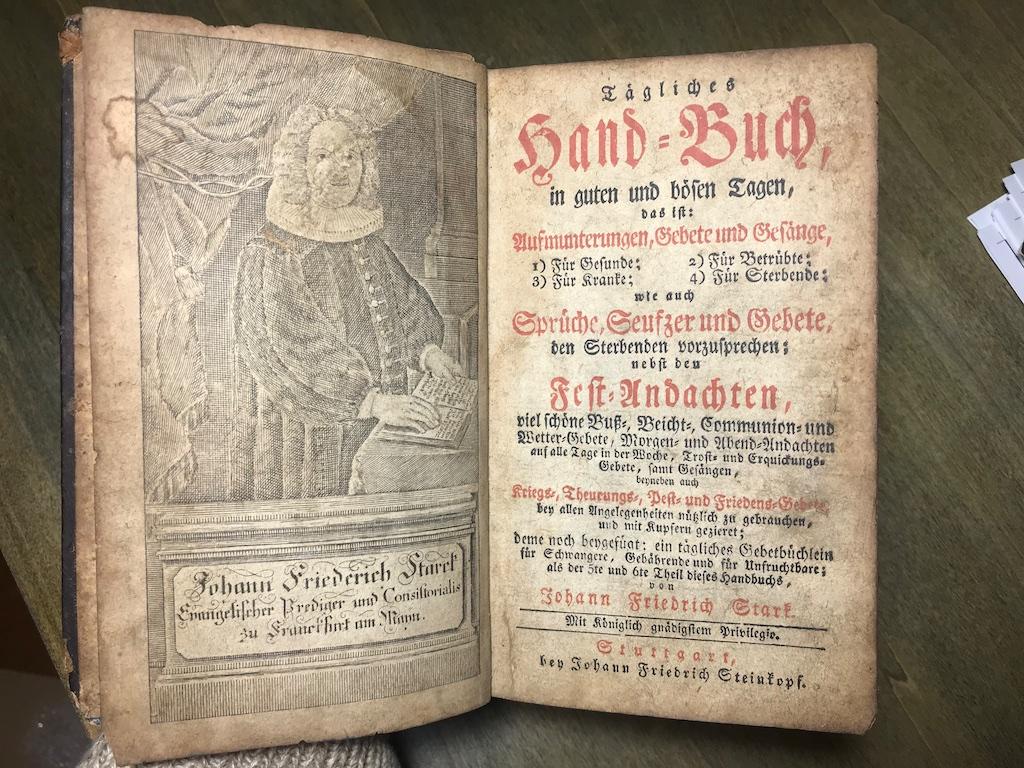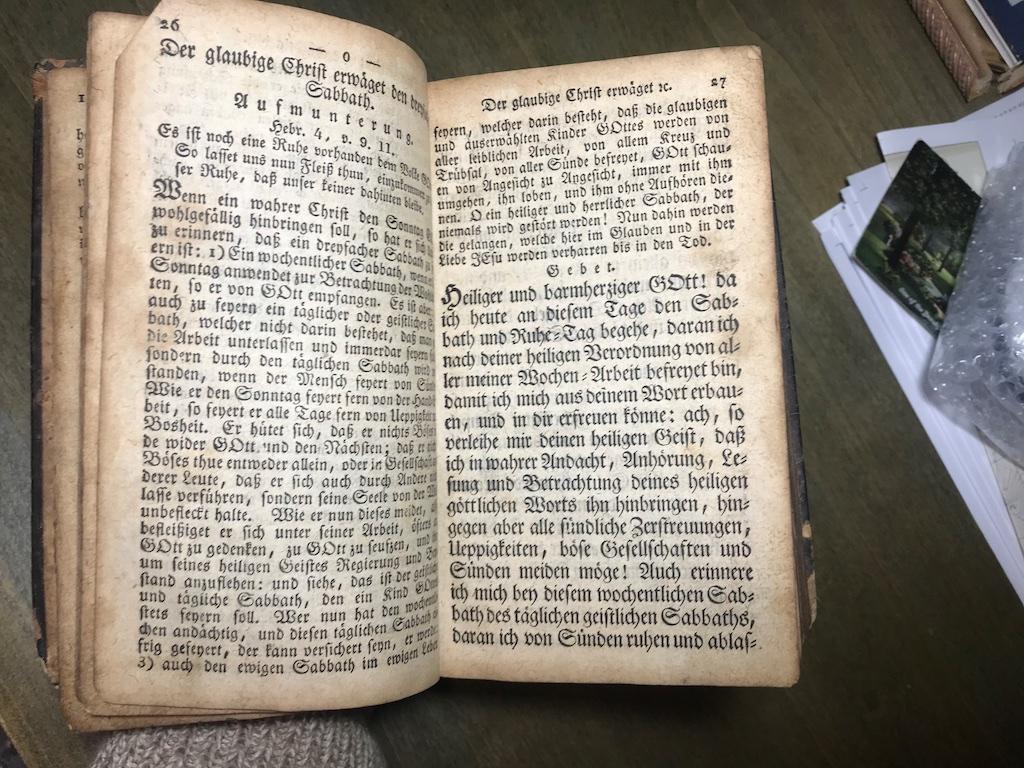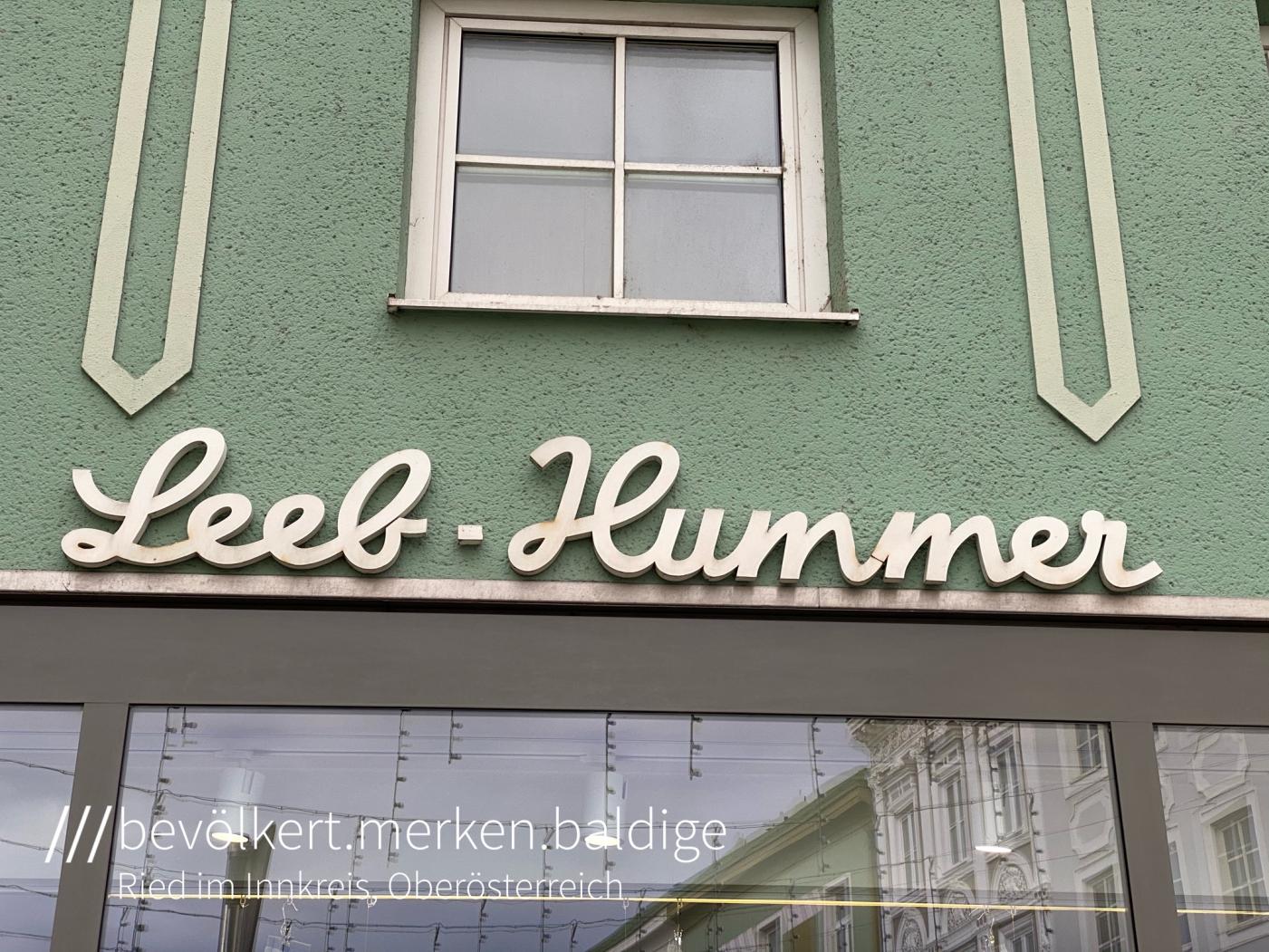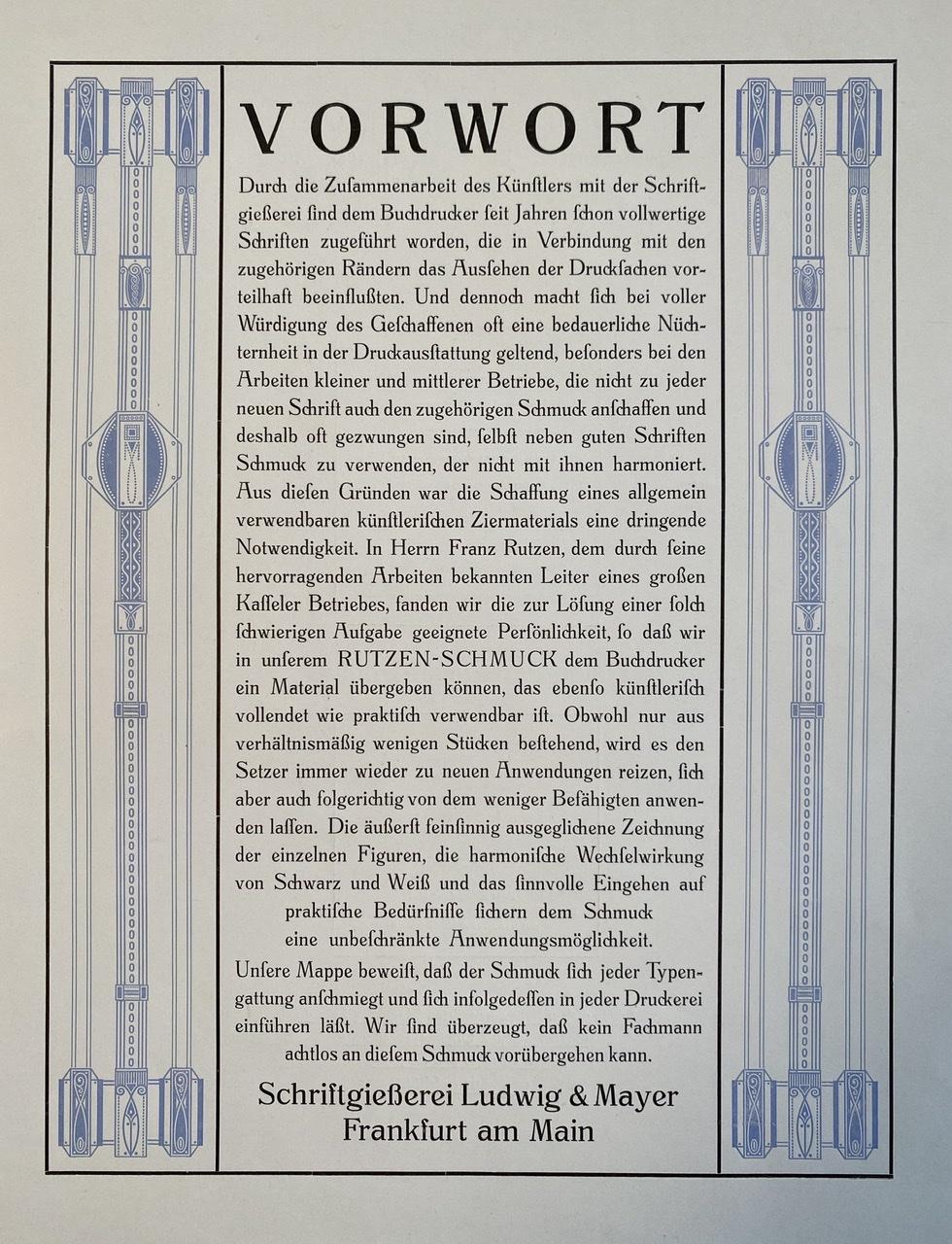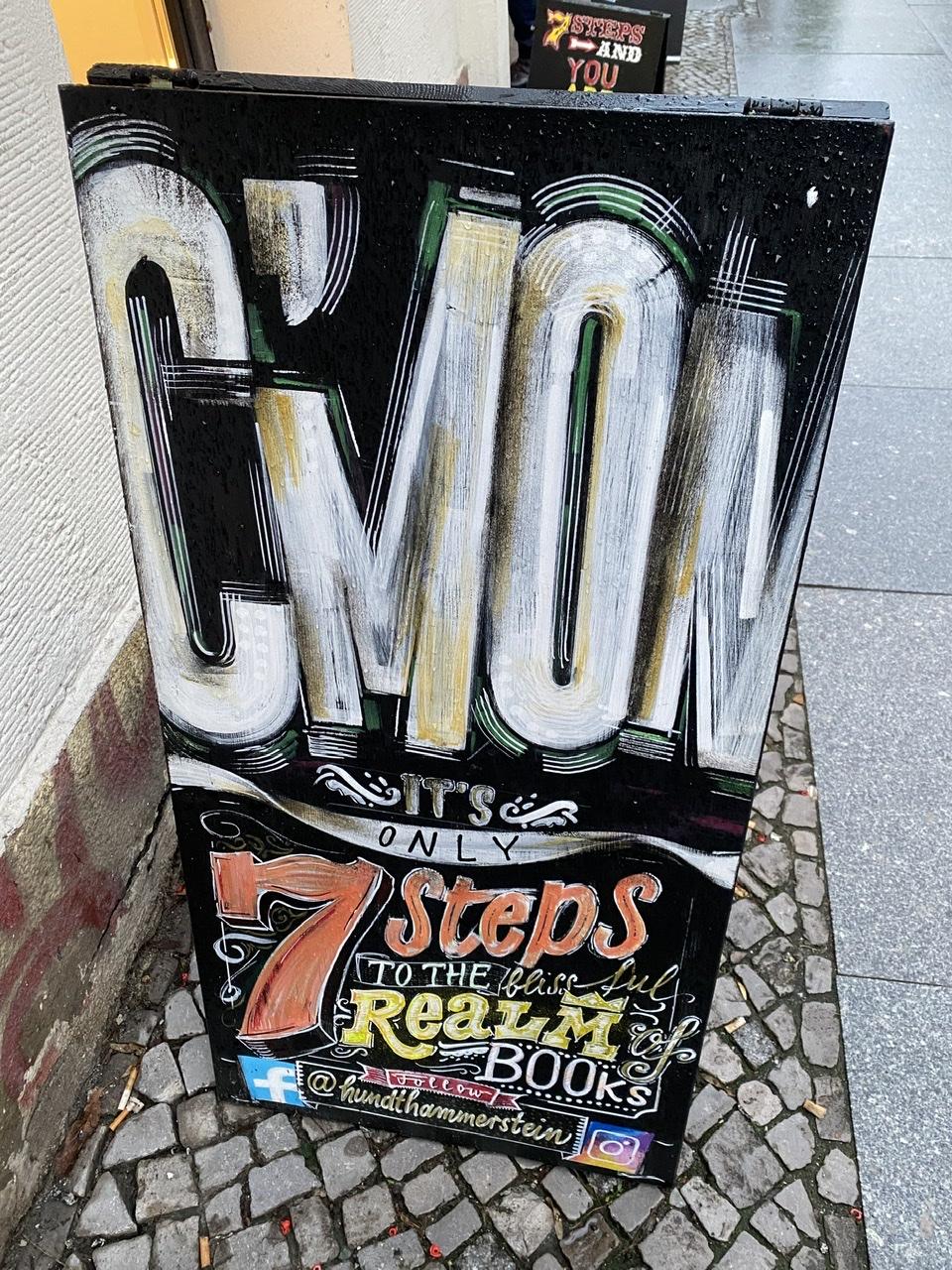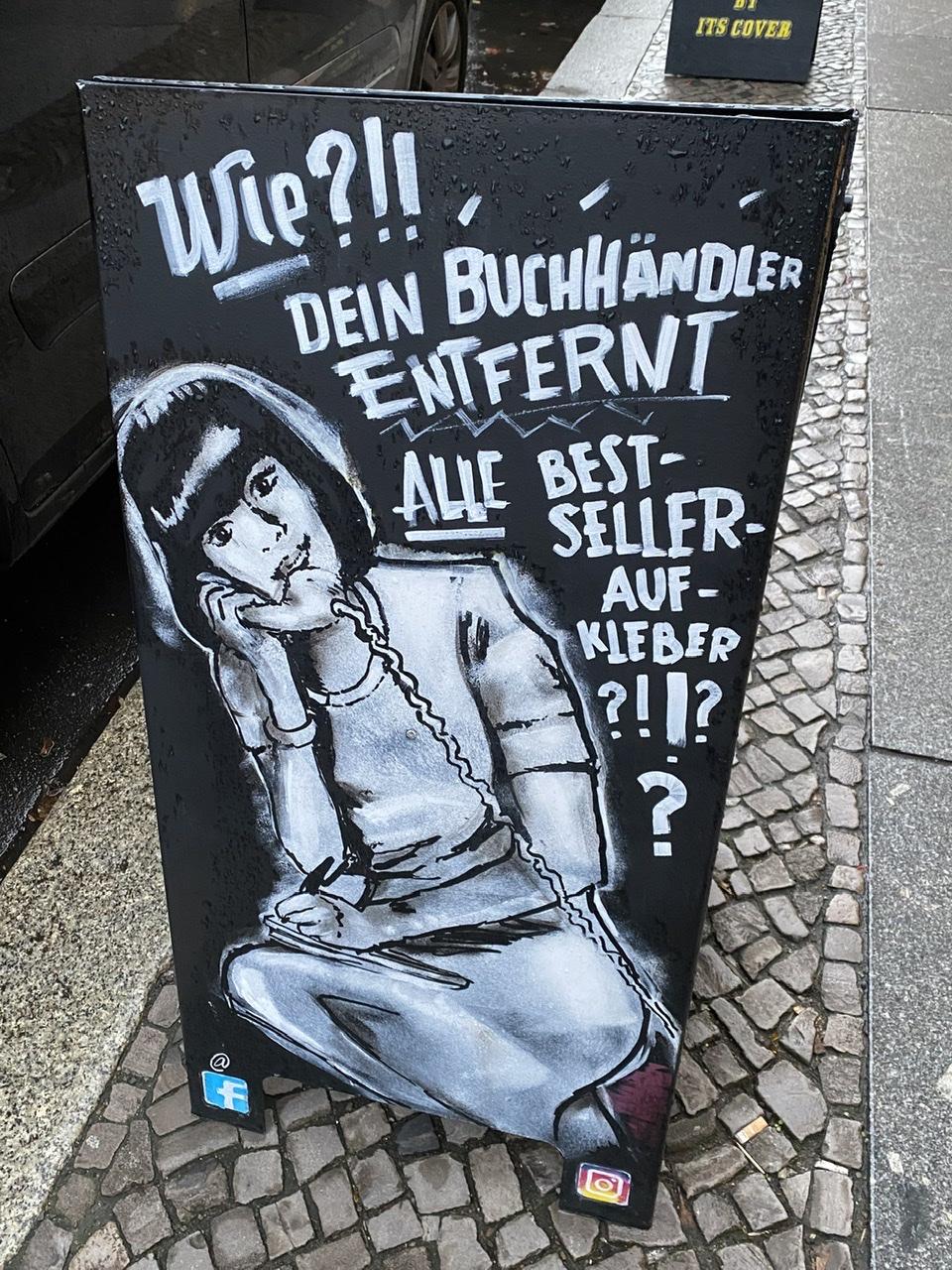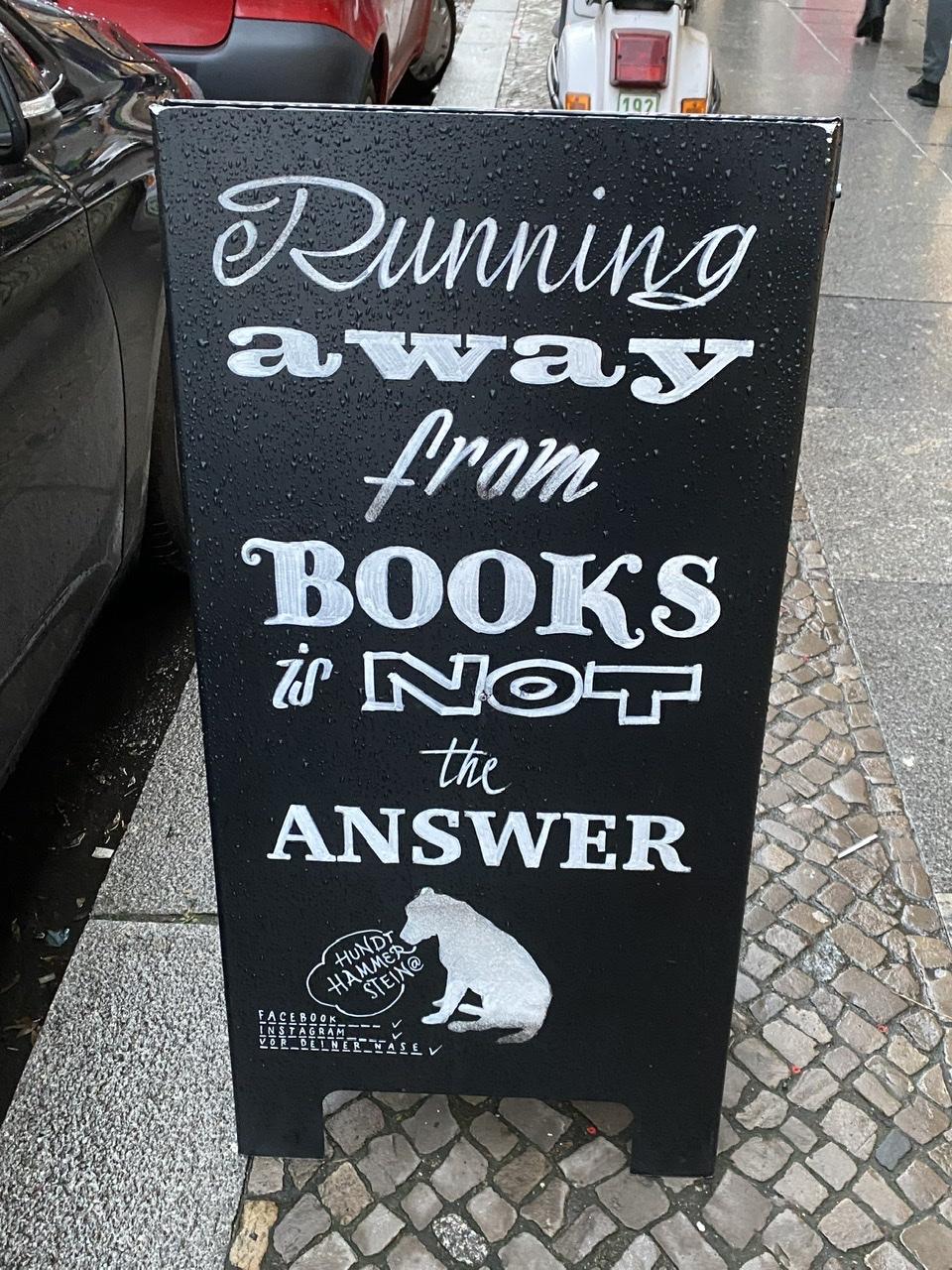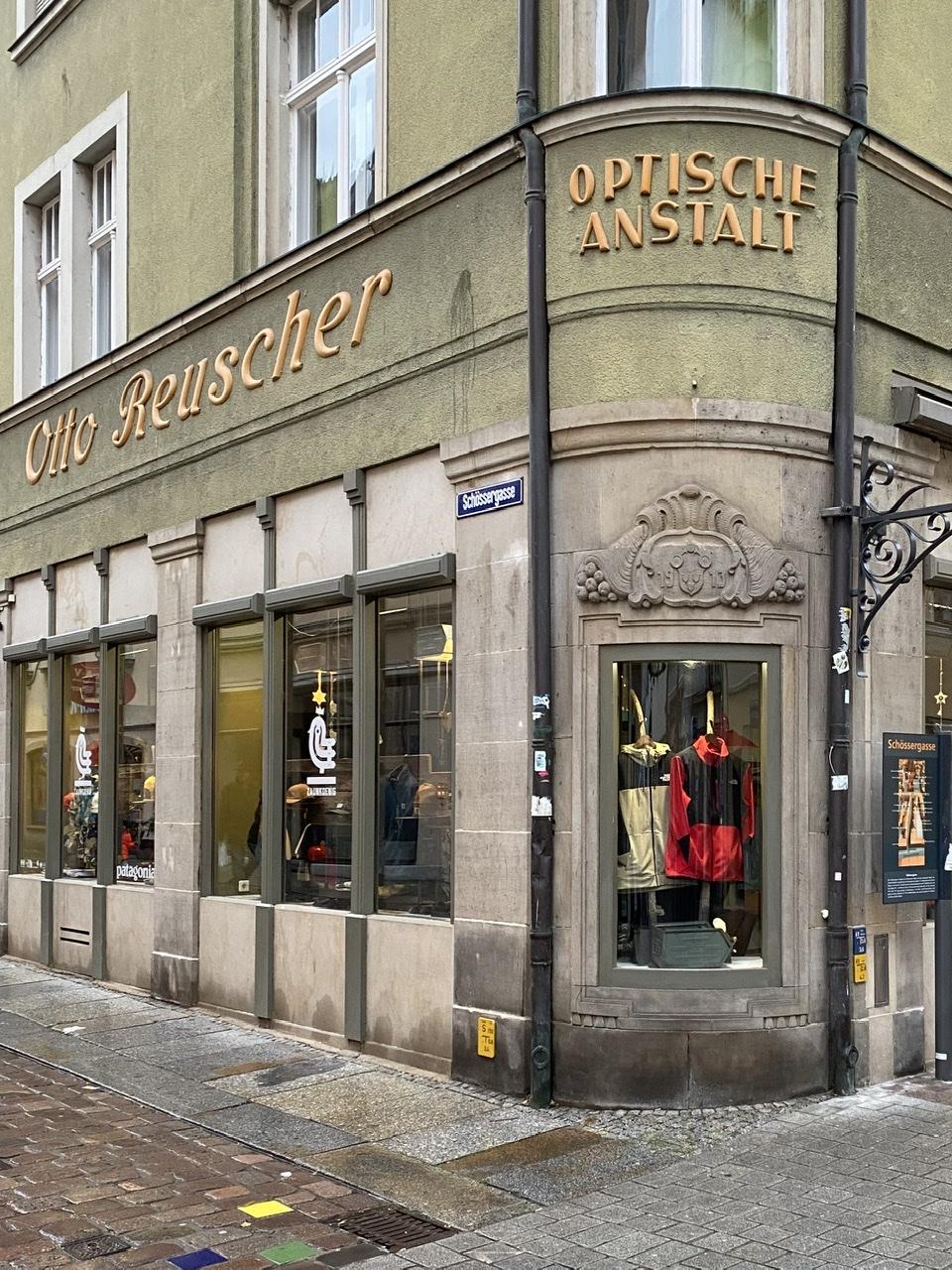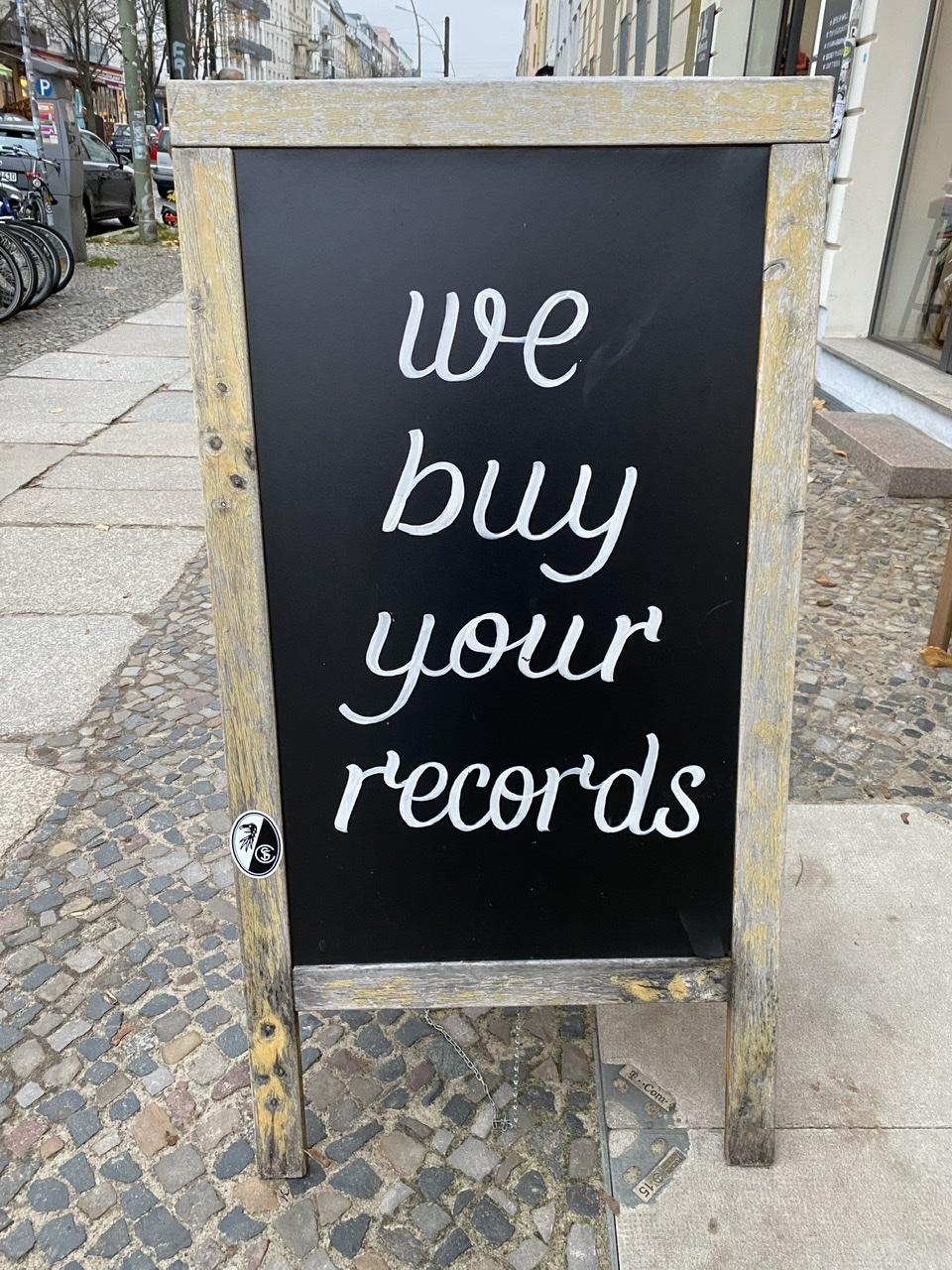
Ich nehm auch immer gern Gemüse mit, besonders fröhlich mit dem passenden Lied, wer kennt es nicht: "Jaaaa, mir san mi'm Radi da,/ jaaa, mir san mi'm Radi da ..."
Vielleicht ne Neuzüchtung, Größe vom Rettich
Mindestens, heißt es doch Willkommen IM ..." *flöt* ;-)
..ne Neuzüchtung.
Dann wäre hier gelungen, woran schon in den späten Sechzigern
rumprobiert wurde:  eine Kreuzung aus roten Kugeln und langen
Weißen . Nur daß damals die Ergebnisse nicht "befriedigend"
waren .
(Ohne damit eine Diskussion lostreten zu wollen …)
Das lange s in freier Wildbahn ... :shock:
Ohne Kontext  hätte ich das immer als f angesehen. Aber mit reichlich
gutem Willen kann ich die Verwendung als langes  s  akzeptieren.
Es ist ja wohl nicht ganz grundlos verschwunden. Als Novität ist es ab und zu erfreulich. In einem Text, den ich des Inhalts wegen lese, würde es mich aber gewaltig stören.
Witzigerweise habe ich die Eſse (?) in dem VORWORT-Text komplett überlesen. Hätte nie gedacht, dass mir das mal passiert!
An bestimmten Stellen überlese ich sie auch. An anderen Stelle bleibe ich sofort hängen ... gerade am Wortanfang.
Gerade in einer Schriftprobe entdeckt, die ich bei Ralf gekauft habe. Reich werde ich mit einer Wiederbelebung bestimmt nicht, aber so aus Spaß mache ich das vielleicht mal.
Ein Kunde hat mir unverhofft ein Buch geschickt mit der Bemerkung, daß ich damit vielleicht mehr anfangen kann als er.
Speckige Schwarte. "H.K. 1851"
Das Innere ist deutlich älter als der Einband. Datum gibt's keins, aber J.F. Steinkopf fing erst 1792 an. Das Buch selbst war wohl weit verbreitet und viel gelesen; seit 1728 erschien es über 150 Jahre lang in vielen Auflagen bei verschiedenen Verlagen.
Inhalt: markante Fraktur in verschiedenen Größen, schön anzusehen. Wenn ich mal Zeit habe, mache ich vielleicht was daraus.
Leeb-Hummer is besser als Toot-Hummer, ist doch logo!
Die Geschichte mit
/// erschließt sich mir jetzt nicht. Soll das jetzt irgendwie bekannt sein, dass das für w3w.co/ stehen soll? :-?
edit: Sehe gerade, dass das tatsächlich so sein soll. Da muss wohl noch einiges an PR geleistet werden. Ich hatte noch nie von dem Laden gehört.
Falsche Präposition! Da sollte natürlich »Neulich [im Angebot]: Sachsen-Anhalt« stehen. Aber wer will schon Sachsen-Anhalt kaufen?¹  :-?
Überraschend auch, dass es schon Mobiltelefone gab, als das Schild aufgestellt wurde. Obwohl, vielleicht war es ja eine Seminararbeit irgendeines Burg-Studenten zum Thema Halbtransparenz auf Holz.
1. Ich komme da her. Ich darf das.
:baeh:
Über die Mobilfunknummer habe ich mich auch gewundert. Passend wäre »Fernruf« plus eine drei- oder vierstellige Nummer ...
Neulich in Sachsen Anhalt ...
Kürzlich in Sachsen ...
Das ging aber flott ...
Anhalt innerhalb von 4 Stunden verkauft ....
*duck&renn* ;-)